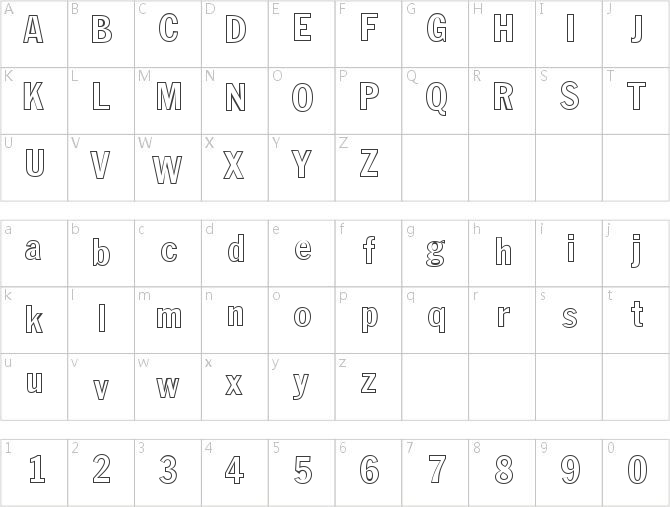
FranklinHeadlineCondOut
FranklinHeadlineCondOut介绍
FranklinHeadlineCondOut字体字库是一款让人赏心悦目、百看不厌的英文字体,适合各类广告和产品包装设计应用,字体大小0.07MB,格式为ttf字体,上传用户是星期一,作者/版权方为未知